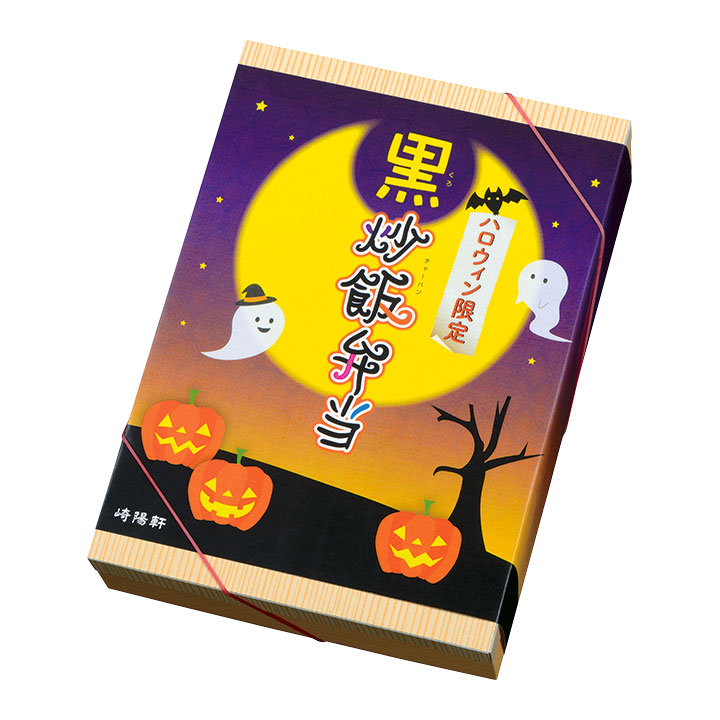
崎陽軒 「ハロウィン限定 黒炒飯弁当」のフォントはダイナフォントクラフト遊とてがき魔を使用
崎陽軒の「ハロウィン限定 黒炒飯弁当」のタイトルにダイナフォントのクラフト遊とてがき魔が使用されている。黒がクラフト遊、炒飯弁当の部分がてがき魔となっている。
クラフト遊
遊び心にあふれる子供が書いた文字をイメージしてデザインされた書体。文字のユニークさや破調が表現されたかわいらしい印象の書体になっている。短い点や線で構成された字形が特徴であり、軽やかさと陽気さに溢れいてる。
てがき魔
西遊記の主要登場キャラクターである孫悟空の「緊箍児(きんこじ)」や「ハリー・ポッターの魔法の世界」などの物語の世界感にインスパイアされ生まれた書体。ちょっと斜めな文字と筆末に残された緊箍児の形が大きな特徴。ストロークの曲線は多様な変化に富み、不思議な感覚が魔法を連想させる。